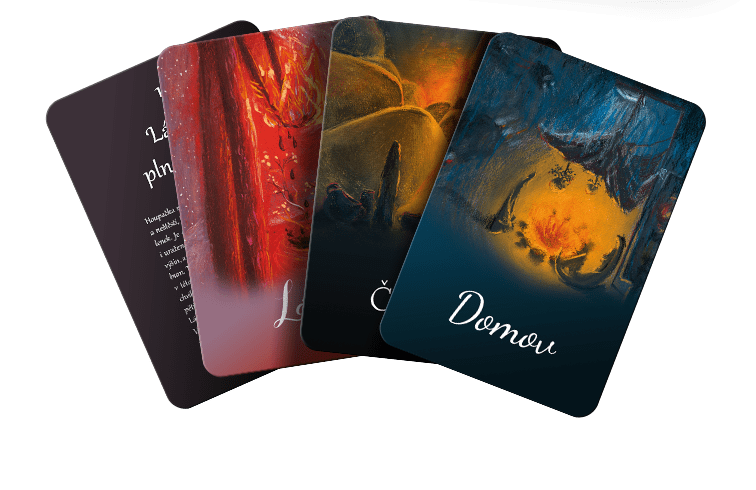
Dobrý personalista by měl (stejně jako psycholog nebo kouč a mentor) být schopen vidět pod hladinu povrchní konverzace, vnímat spodní proudy, které sem tam napovrch vyplaví tu pravou podstatu člověka, a které definují jeho charakter a potřeby. U otevřených, komunikativních lidí to jde lehce, oříškem bývá člověk málomluvný, uzavřený, introvertní, ze kterého jen těžko dostáváte tři souvislé věty najednou. A personalista má velmi omezený čas, aby zjistil:
- jeho potenciál, který by mu umožnil ten nejpřímější a nejrychlejší osobní i profesní růst,
- jaké potřeby, které by mu měla firma naplnit, aby se cítil ohodnocený a loajální,
- jestli má ambice růst, nebo mu ke štěstí úplně stačí pravidelnost a zázemí,
- jestli potřebuje motivaci zvenku nebo jenom podpořit tu vnitřní,
- jak zapadne nový člověk do kolektivu, do kterého vstoupí.
Když jsem před pár lety nabírala lidi do mého oddělení, říkala jsem si, co by mi pomohlo dostat se snadněji pod slupku těch, kteří si drželi odstup. Stejně tak při ročních hodnotících pohovorech by ch přivítala pomocníka, který by odlehčil situaci hodnotím/jsem hodnocený a přispěl k tvůrčímu dialogu. Odpovědi jsem našla až za hodně dalších let, v době, kdy jsem začala studovat neverbální řeč fontů a byla jsem fascinovaná tím, kolik výběr písma o člověku prozradí. Stejně jako grafologie. A tak jsem se o to rozhodla podělit. Vytvořila jsem speciální karty. Nemyslím tarotové karty, ale karty, které otevírají díky fontům lidské podvědomí a vytvoří most k pochopení. Pochopení, koho máte před vámi, jaké má váš partner potřeby, touhy a nastavení a jestli se potkává s tím, co mu můžete nabídnout.
Jak karty Fontohrátky pomáhají personalistům, koučům nebo psychologům?
V balíčku karet je 8 témat, které jsou prostředkem k odstranění bariér v komunikaci.
- Důvěra
- Čekání
- Kreativita
- Naděje
- Domov
- Láska
- Smutek
- Radost
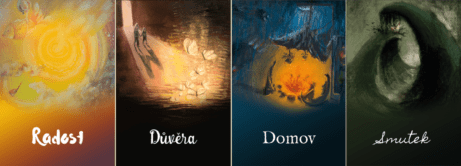
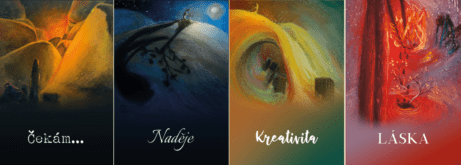
Každé téma je zastoupené 4 kartami se stejnou ilustrací, ale jiným fontem.
Jak s kartami přesně pracovat?
1/ Vyberte si jedno z osmi témat, které vás zajímá.
Pokud potřebujete jenom prolomit ledy, můžete nechat téma vybrat člověka, se kterým pohovor (mentoring, hodnocení,…) děláte.
2/ Nechejte člověka vybrat jeden ze čtyř fontů daného tématu a zeptejte se, proč ho přitáhlo právě toto písmo.
Tím, že se bavíte o písmenkách, používáte zkratky k podvědomí člověka. V hodnocení písmen se odráží jeho vztah k tématu.
Například: líbí se mi rozházená písmenka, protože potřebuji různorodost a změnu.
3/ Použijte myšlenky z textu na zadní straně karty, abyste rozvinuli diskuzi.
Text na zadní straně každé karty popisuje dané téma z pohledu energie fontu, který je z čelní strany. Pokud si člověka přitáhne font extrovertů, bude mu blízký i text, ve kterém se odrazí způsob, jak vnímá kreativitu právě člověk otevřený a komunikativní. Anebo ho naopak bude iritovat. „To vůbec nejsem já“. Obojí je skvělá příležitost, jak rozvinout hovor na velmi osobní úrovni, která vám umožní poznat během pár minut vnitřní svět člověka před vámi, i když ho možná u pohovoru velmi dobře skrývá.
Můžeme si to ukázat např. na tématu kreativity.
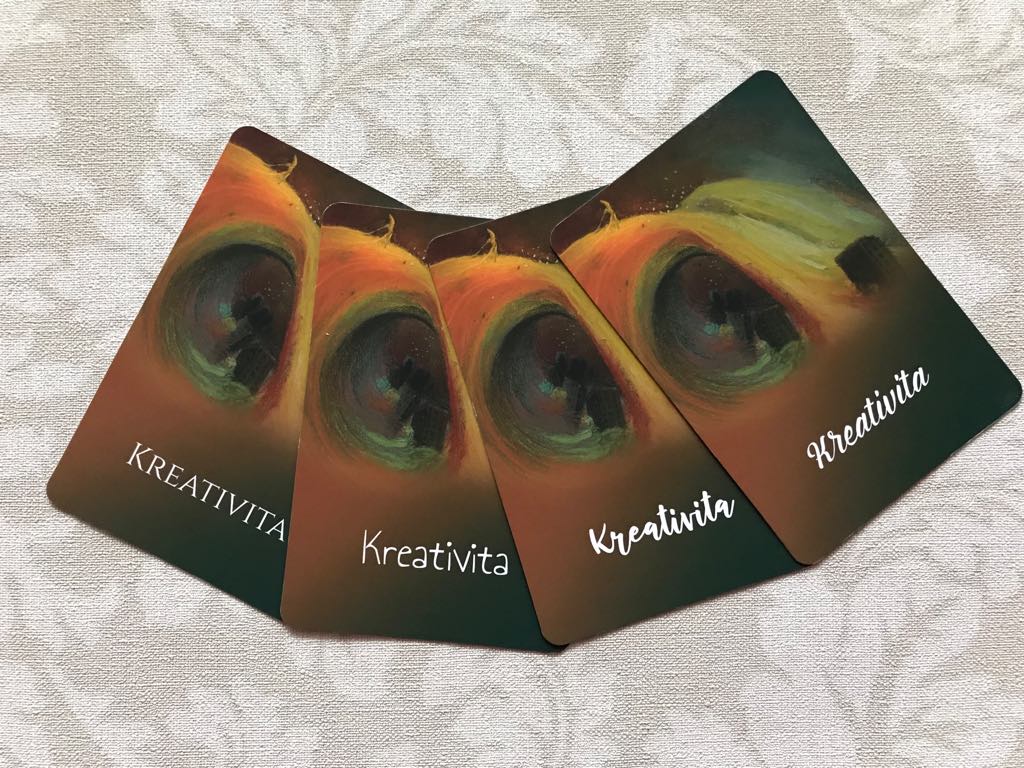
Na co nám téma kreativity pomůže odpovědět?
- Jakým způsobem rád pracuje, v čem má flow?
- Potřebuje, aby jeho práci ocenili druzí a využívali ji anebo mu plně stačí ponořit se do ní a nevnímat svět?
- Tvoří systematicky a dokáže výsledky srozumitelně prezentovat anebo je jeho práci vlastní tvůrčí chaos?
- Potřebuje být členem teamu anebo tvoří raději sám?
Zkuste si sami vybrat jeden ze 4 fontů pro kartu kreativity a poté si přečíst, jestli vzkaz na druhé straně sedí:
1/ Kreativita jedinečnosti – cokoli dělá, dělá po svém, ale za výsledky se může zaručit. Nepustí ven nic nedokonalého, bude vše ladit do posledního detailu. Většinou má velké znalosti, inteligenci a talent. To vše dokáže spojit dohromady, ale občas mu chybí sebedůvěra a průbojnost. Pokud ji podpoříte, a necháte mu volnou ruku, máte ve firmě poklad.
2/ Kreativita extrovertů – miluje komunikaci, je akční a málokdy je introvert. Nestojí o jedinečnost, potřebuje pracovat pro lidi a s lidmi a vědět, že to, co tvoří, jim pomůže. Pak je schopný pracovat 24 hodin, aniž by si toho všimnul. Potřebuje nutně práci v kolektivu, zavřete ho někam o samotě a zblázní se.
3/ Kreativita umělců – je náladový, někdy nevypočitatelný, v kolektivu oblíbený i nenáviděný. Je schopen pětkrát zadání přepracovat, dokud s ním nebude vnitřně spokojený. Výsledek bude osobitý, nekopírovatelný a přesvědčivý. Nutně potřebuje kreativní profesi, posaďte ho k tabulkám a grafům a buď vám je předělá do barev anebo uteče.
4/ Kreativita řízená – skvěle dokáže skloubit kreativitu, rozum a svědomitost. Nestrpí chaos a nepořádek, budou mít vždy dokonale uklizený stůl a mají úžasný smysl pro detail. Na rozdíl od ostatních většinou přesně ví, jak se dopracovali k výsledku a dokáží tuto cestu popsat a výsledek zopakovat. Ideální rekruti pro školitele, lektory, mistry, všude, kde mají učit druhé.
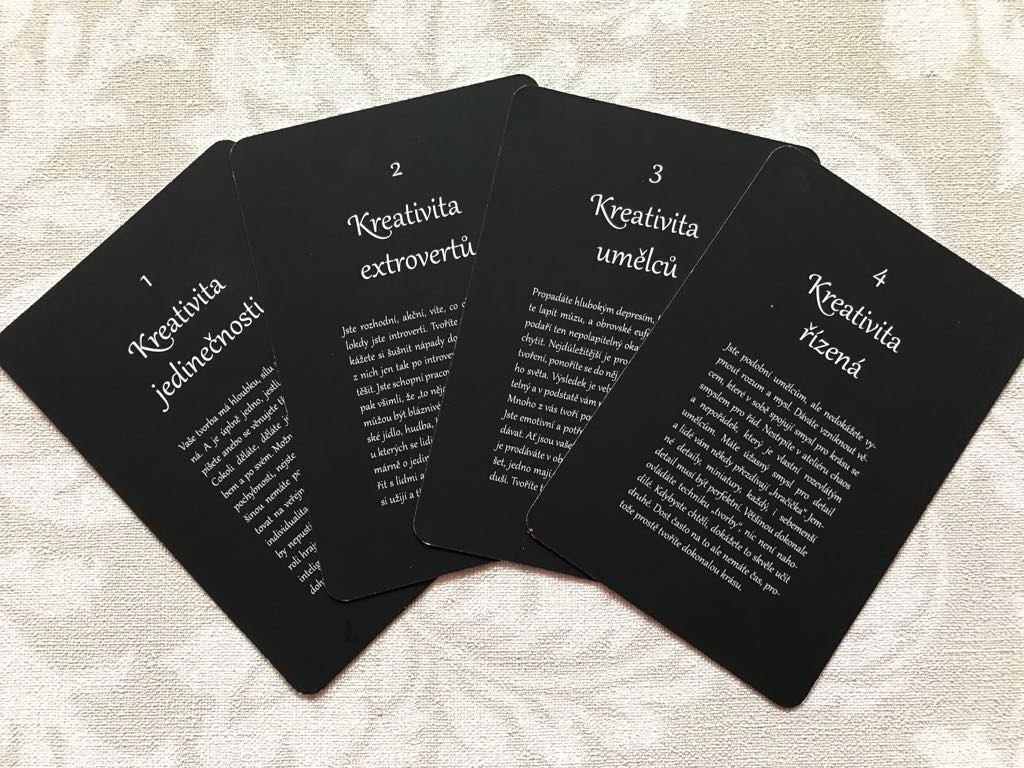
Jaká další z témat vám mohou posloužit?
Důvěra – Vztahy k druhým
Jak moc mu můžete věřit a jak moc důvěřuje on druhým? Je nevěřící Tomáš anebo naivní Maruška? Zlomový moment při volbě manažera. Bude umět delegovat a dávat důvěru anebo si všechno raději udělá sám nebo bude vyžadovat bezmezné dodržování předpisů?
Za těch pár týdnů, co jsou karty na světě, se osvědčily jako skvělý nástroj pro hlubší komunikaci. Nejsou všemohoucí, neukážou vám budoucnost nebo charakter člověka, jsou pouze nástroj.
A jako každý nástroj, i lopata nebo kolo, karty jsou užitečné pouze v rukách člověka, který je umí správně použít.